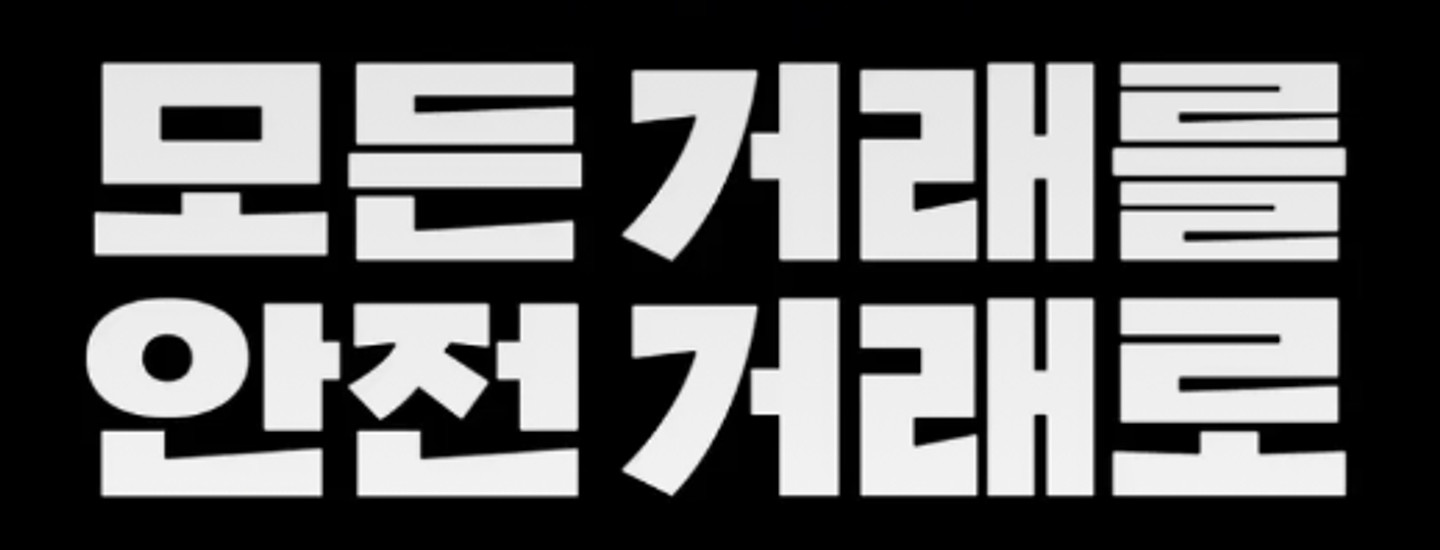
무슨 폰트인가요??ㅜㅜ
폰트가 궁금합니다!!
폰트 알 수 있을까요,,
폰트 변형인지.. 무슨 폰트인지 아시는분 있으시다면 알려주세요 ㅠ
이 폰트가 무엇인지 알려주세욧!
폰트 찾기를 돌려봐도 정확하게 일치하는 폰트가 없습니다. 'ㅌ' 모양이 특이해서 금방 찾을 줄 알았는데...아시는분 계신가요?
무슨폰트인지 아시나요 좀 알려주세요
옛날 방송 자막으로 많이 쓰였던 폰트 같은데 무슨 폰트인가요?
이건 무슨 폰트일까요 ㅜㅜ 두 시간째 찾고 있어요
무슨폰트인지 궁금해요~
어떤서체일까요!? 도움부탁드립니다
가로로 길게 늘린 느낌의 영문 폰트
어떤 폰트인가요??